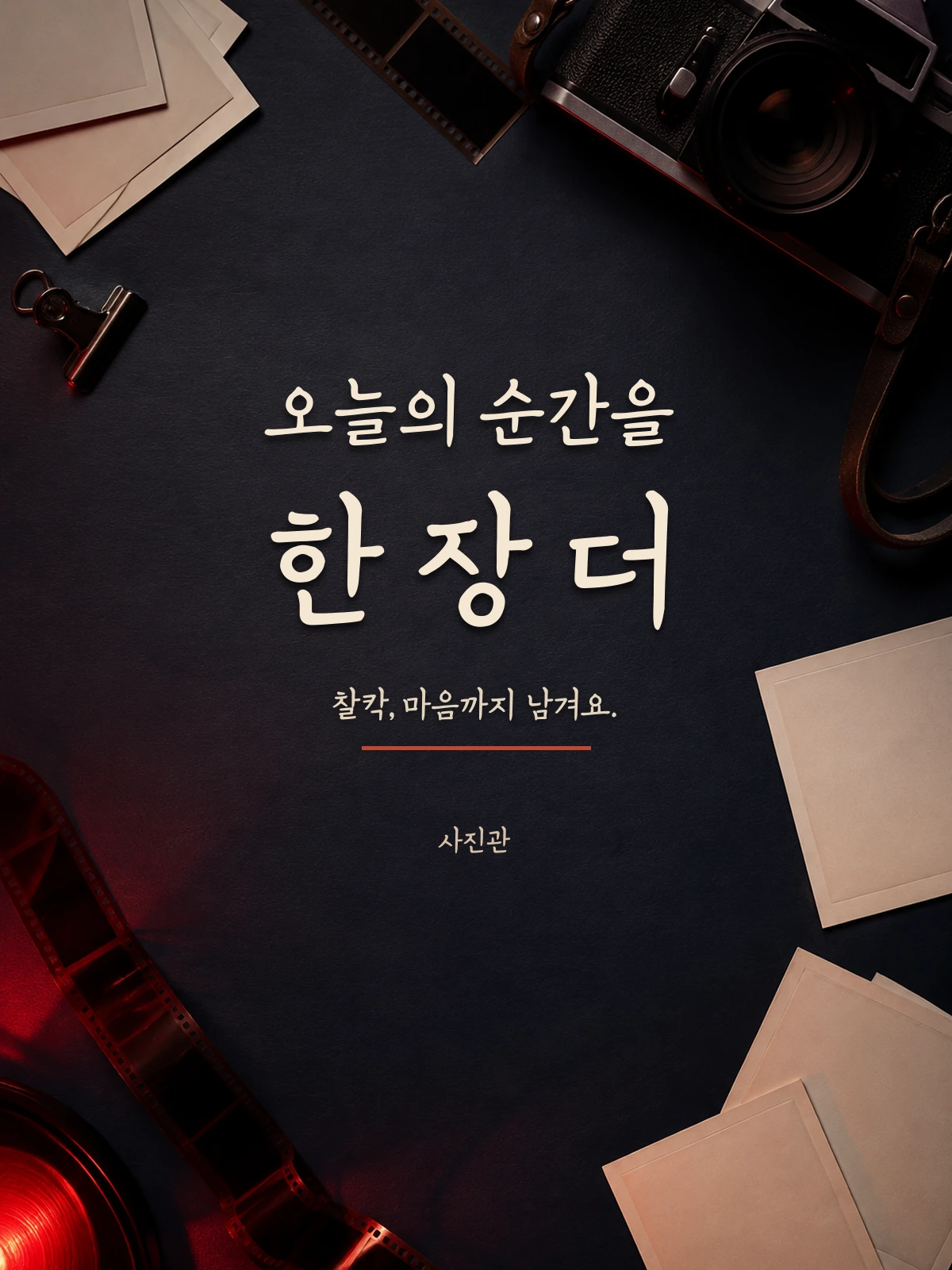
사진관 — (주)와이즈폰트에서 배포하는 무료 폰트입니다. 사진관에서 직접 써 내려간 듯한 자연스러운 획과 정겨운 필기감이 돋보이는 손글씨체
와이즈폰트의 손글씨 서체로, 장식 없이 필기감만 남긴 것이 특징입니다. 하트나 별 같은 그림이 들어가지 않아 같은 회사의 다른 손글씨체보다 쓰임이 넓습니다.
파일에서 재어 보면 받침 유무에 따른 높이 차가 거의 없어 손글씨인데도 네모틀에 가깝습니다. 낱자는 폭보다 높이가 커서 세로로 선 인상이고, 세로획이 가로획보다 약간 굵어 펜으로 눌러 쓴 느낌이 납니다.
글줄이 가지런하게 떨어지는 손글씨체라 제목뿐 아니라 짧은 본문에도 얹을 수 있습니다. 사진 위에 올리는 캡션이나 앨범 표지의 한 줄처럼, 손글씨의 온기는 필요하지만 산만해지면 곤란한 자리에 맞습니다. 현대 한글 11,172자를 모두 담았고 굵기는 하나입니다.